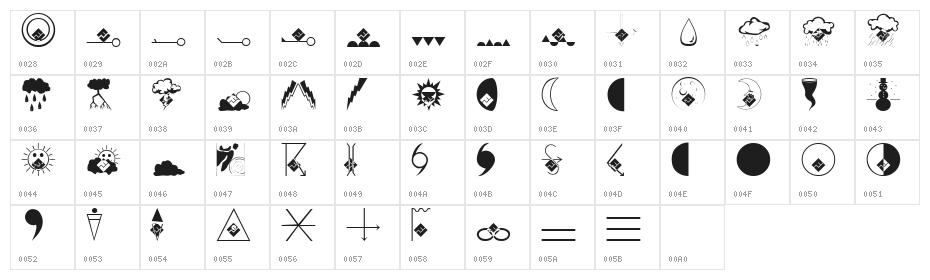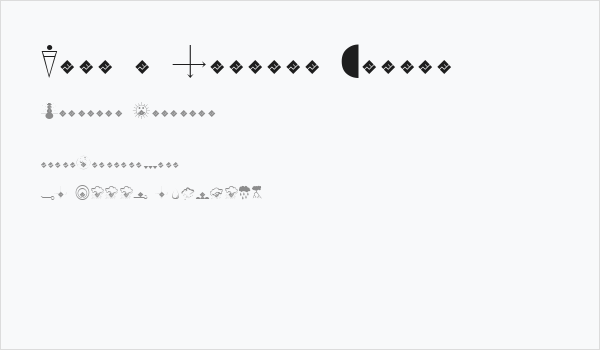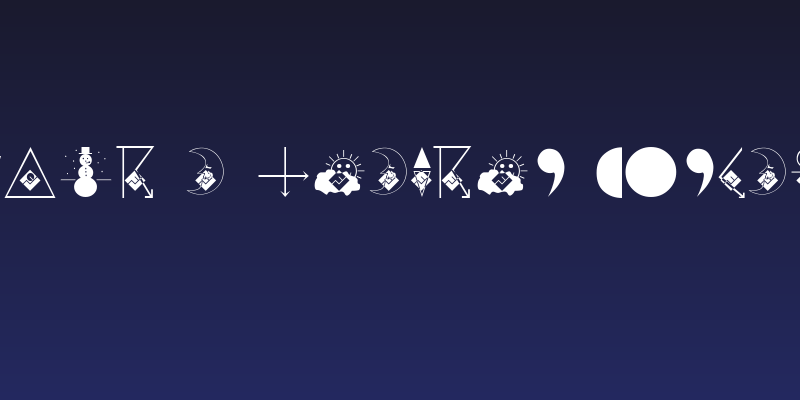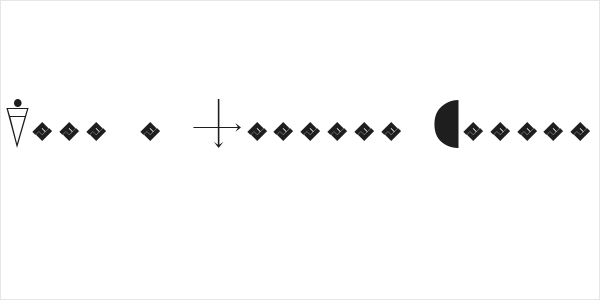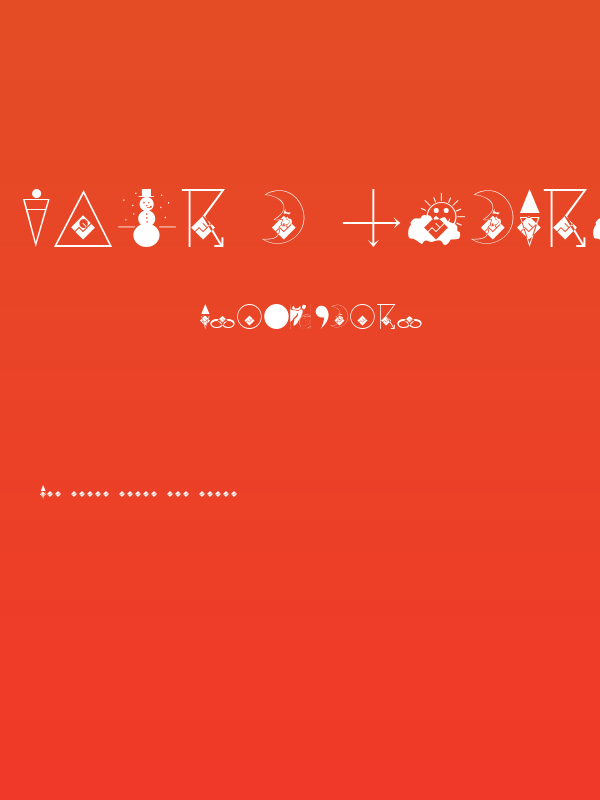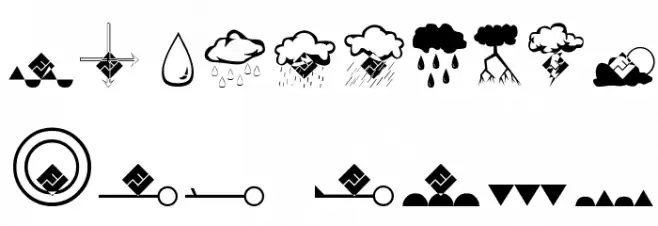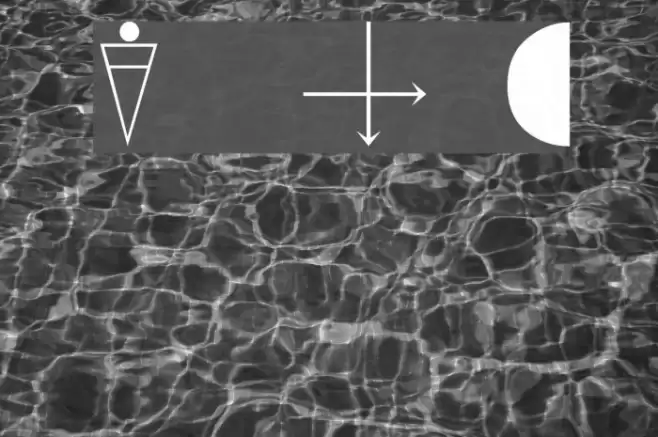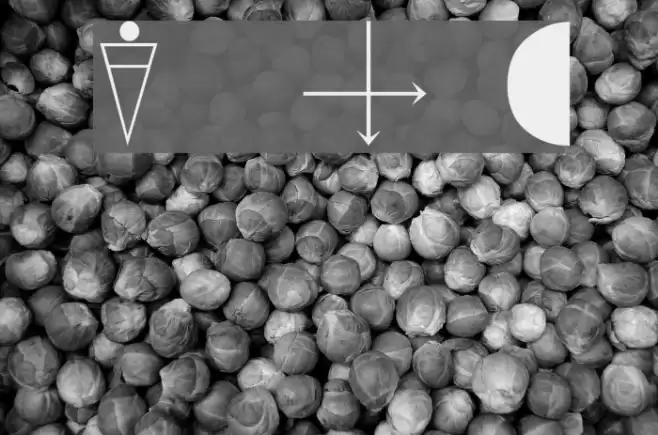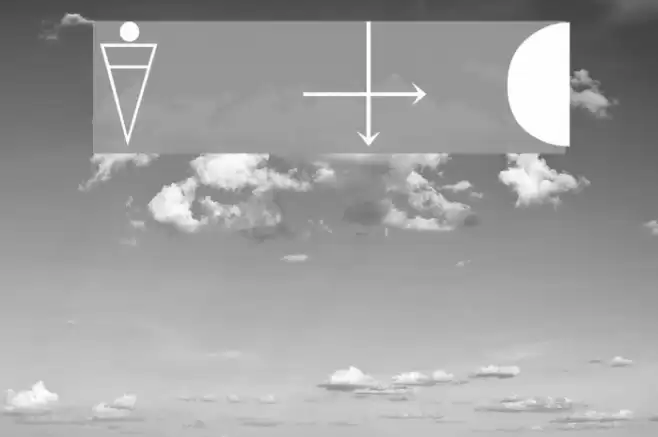
Such a Weather Normal Font
✎ Cartoon
| カテゴリ | Cartoon |
| 全体的なスタイル | Decorative, Playful, Thematic |
| 用途 | Icons, Infographics, Themed Headlines, Branding |
| おすすめプロジェクト | Weather apps, educational materials, infographics, themed posters, children’s books, branding for outdoor or environmental organizations. |